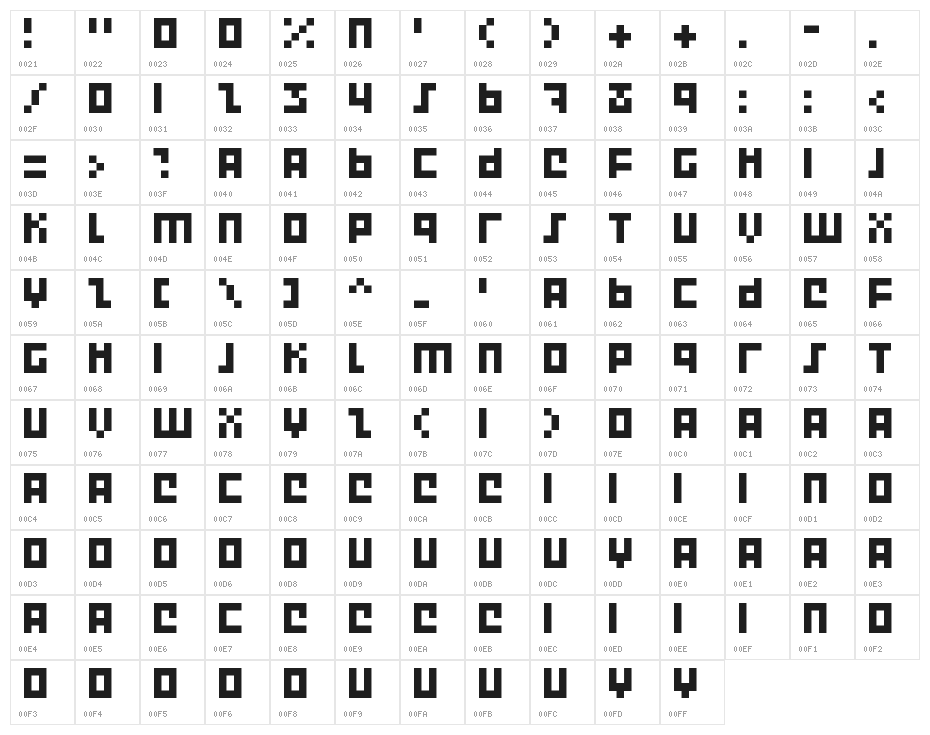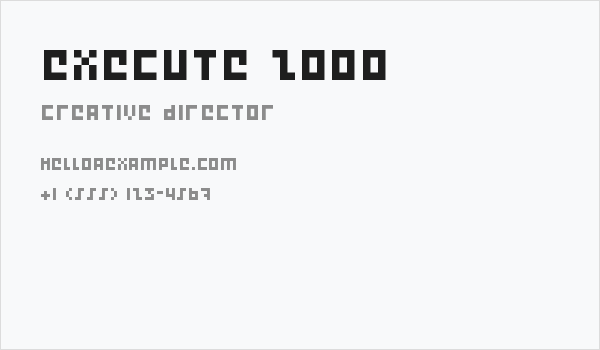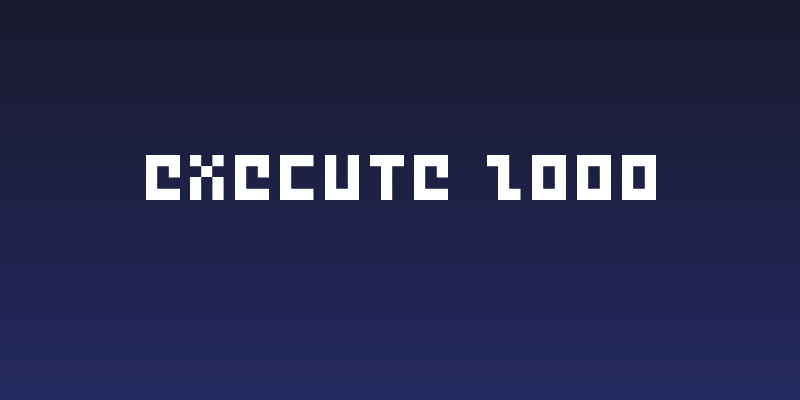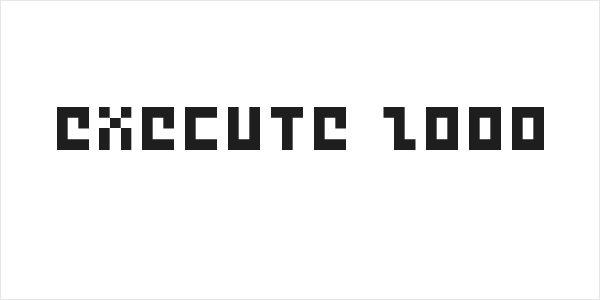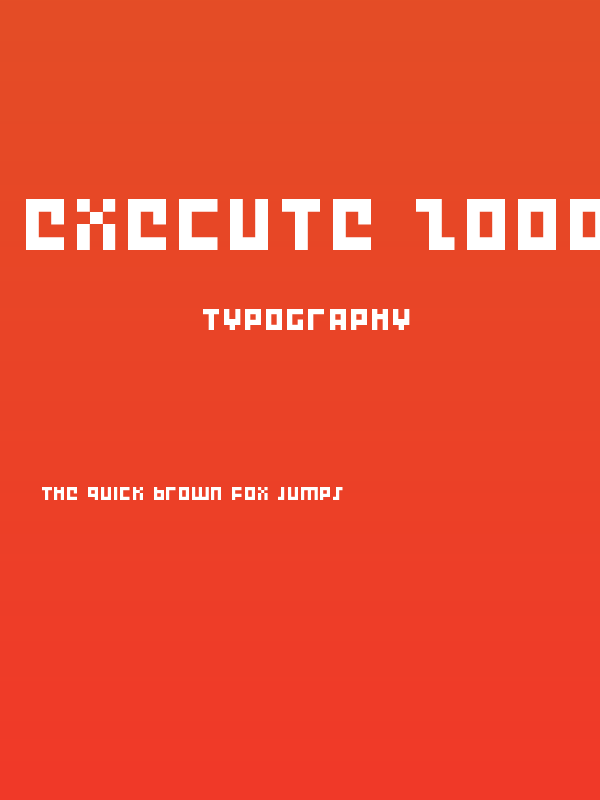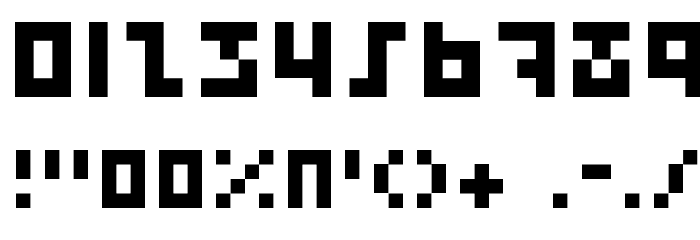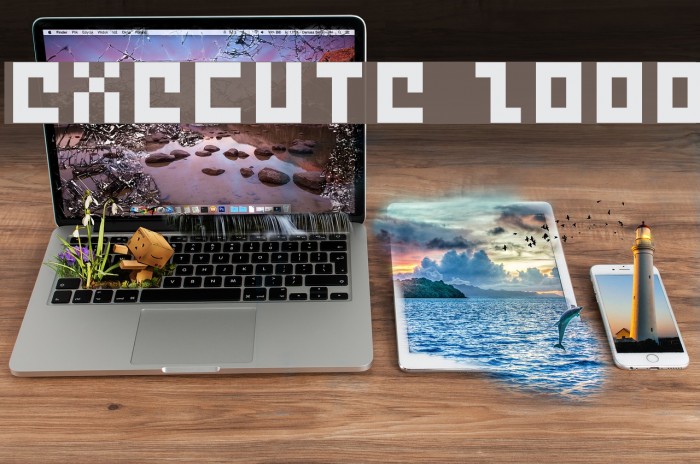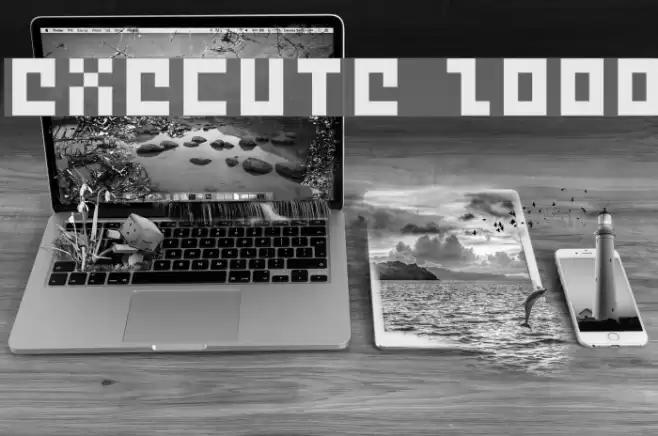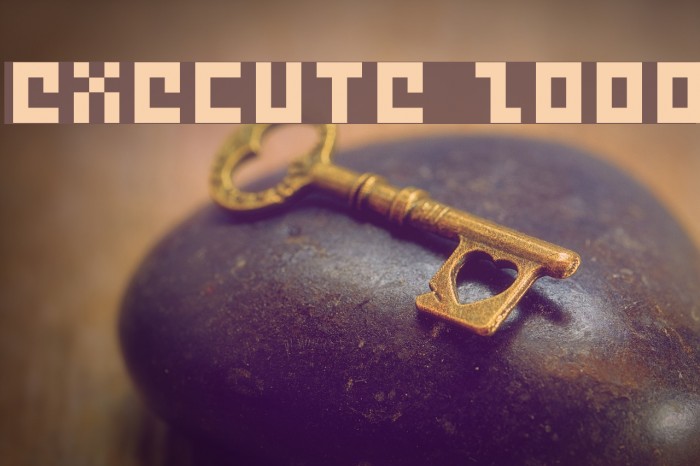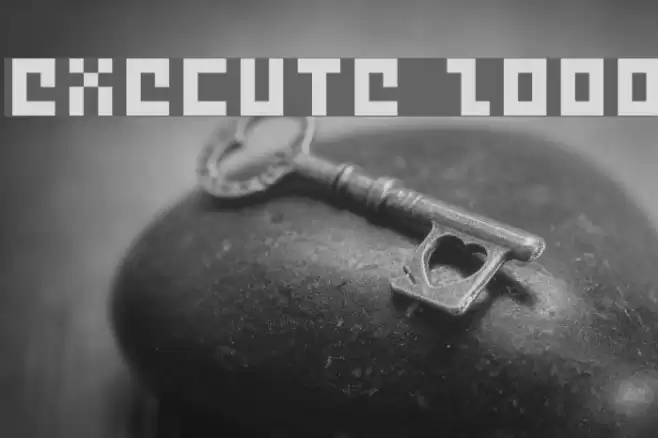
Execute 2000 Font
✎ Pixel
| Categorii | Pixel |
| Stil general | Retro, Digital |
| Proiecte propuse | Ideal for retro video game graphics, digital art projects, tech-themed posters, or any design requiring a nostalgic digital feel. |